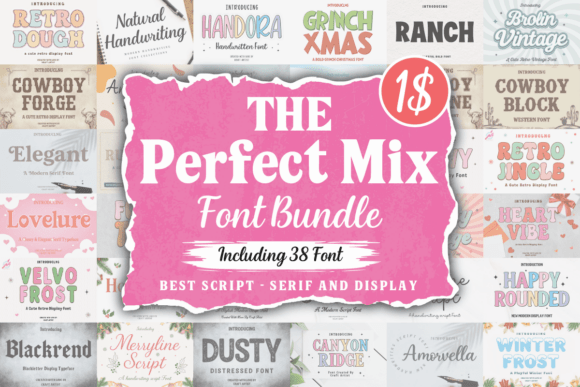
The Perfect Mix Font Bundle
Trouver les bons éléments de conception peut être un défi, mais The Perfect Mix Font Bundle propose une collection exceptionnelle qui rehausse instantanément votre travail.
Que vous créiez des produits POD (impression à la demande), des invitations de mariage ou des visuels pour les réseaux sociaux, The Perfect Mix Font Bundle est un choix idéal.